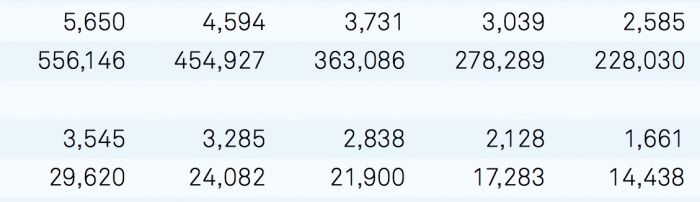
Welche Kombinationsschrift zur Input Sans (Font Bureau)
um nicht im eigenen Saft zu ertrinken, die Frage in die Runde: welche Schrift könntet ihr Euch für den Fließtext in Kombination zur Input Sans (Headline-Einsatz) vorstellen?
Um den Schwierigkeitsgrad noch etwas zu erhöhen – es sollte vorzugsweise auch ein serifenloser und wenn möglich nicht all zu teurer Font (max. 40,– € pro Schnitt) sein.
(Thema: Umwelttechnik, Ingenieurwesen)
Nachtrag: Meine Gedanken schwirren momentan in Richtung Univers (wirkt irgendwie abgestanden), Facit, FF DIN … hmmm.
Außerdem wird es eine zweite Variante in der FF Unit ohne Schriftmischung geben.
So – hat sich erledigt. Bin sowohl von der Input als auch von der Schriftmischung für dieses Projekt weg. Das wird zu kompliziert und die Input scheint mir ein eher schwer zähmbares Exemplar zu sein.
Könntet Ihr mit ruhigem Gewissen die Akkurat als Unternehmensschrift (auch Tabellen und Fließtext-Passagen, Druck und Web)  empfehlen, oder erlebt man da irgendwann das böse Erwachen? Ich finde formal ist sie eine echte Hausnummer, nur der Ausbau (z.B. fehlende Ziffernvarianten) bereitet mir ein wenig sorgen.
Also der Font (akkurat) scheint tatsächlich nicht viele Ziffernvarianten mitzubringen, wobei jetzt auch nicht so schnell rauszubekommen ist, ob die Basisversion proportionale oder Tabellenziffern mitbringt; wenn Dir die Schrift formal gefällt, ließe sich durch die Ergänzung mit der Mono-Version dieses Manko vielleicht beheben, weil da die Ziffern wohl auf jeden Fall tabellentauglich wären, würde sich wahrscheinlich auch stilistisch nicht schlecht machen (worum ging es: Ingenieure – die müssten ja darauf stehen). Prinzipiell würde ich Schriften von Grafikern ja erst mal misstrauen (ist die FF Unit denn noch im Spiel eigentlich).
Gut ausgebaute Alternativen müsste es eigentlich eine ganze Reihe geben, die so auf die älteren Grotesk-Modelle zurückgreifen (FF Bau zum Beispiel, vielleicht die Atlas Grotesk bei commercial type)
Von der Schriftmischung scheinst du abgekommen zu sein; vielleicht wär es ja auch einen Versuch wert, für Headlines etwas dezidiert ingenieurhaftes wie OCR-A oder -B für Überschriften oder Initialen mit einer Antiqua als Textschrift zu mischen (und auch da nichts humanistisches, sondern eher Modell Bodoni).
, für Headlines etwas dezidiert ingenieurhaftes wie OCR-A oder -B für Überschriften oder Initialen mit einer Antiqua als Textschrift zu mischen
oder die isonorm?
Ja, genau, so die Richtung für Schaugrössen, und eine richtige Schrift für Texte, wie ganz oben schon angedacht war.
Gerade drüber gestolpert, weil der Herr Übele gerade einen Newsletter verschickt hatte: Die Helsinki, sozusagen die finnische bzw. Übelesche DIN, das ginge dann wirklich mehr in Richtung Unternehmensschrift. http://www.ludwigtype.de/fonts/helsinki/overview … (gut ausgebaut und jede Menge features, & was ich ganz bemerkenswert finde, daß er ausserdem „Demofonts“ anbietet, also Schriftschnitte nicht nur im Fensterchen online zum Ausprobieren, sondern auch für Layoutzwecke versendet).
Könntet Ihr mit ruhigem Gewissen die Akkurat als Unternehmensschrift (auch Tabellen und Fließtext-Passagen, Druck und Web)
mittlerweile gibt es doch echt viele alternativen zur akkurat, du hast doch die ganzen listen angelegt :huhu:
die nitti grotesk z. b.
Also der Font (akkurat) scheint tatsächlich nicht viele Ziffernvarianten mitzubringen, wobei jetzt auch nicht so schnell rauszubekommen ist, ob die Basisversion proportionale oder Tabellenziffern mitbringt; wenn Dir die Schrift formal gefällt, ließe sich durch die Ergänzung mit der Mono-Version dieses Manko vielleicht beheben, weil da die Ziffern wohl auf jeden Fall tabellentauglich wären, würde sich wahrscheinlich auch stilistisch nicht schlecht machen (worum ging es: Ingenieure – die müssten ja darauf stehen). Prinzipiell würde ich Schriften von Grafikern ja erst mal misstrauen (ist die FF Unit denn noch im Spiel eigentlich).
Gut ausgebaute Alternativen müsste es eigentlich eine ganze Reihe geben, die so auf die älteren Grotesk-Modelle zurückgreifen (FF Bau zum Beispiel, vielleicht die Atlas Grotesk bei commercial type)
Vielleicht haben wir ja Glück und die Tabellenziffern finden sich auch in der Pro-Version. Ich hake noch mal bei der Foundry nach. Zusätzlich die Monoschnitte erwerben wäre zwar für das Erscheinungsbild ein passender Ansatz, das könnte aber dann doch das Budget sprengen.
Bzgl. FF Bau suche ich weniger nach Helvetica-Alternativen, sondern vielmehr eine Schrift mit Betonung der Senkrechten (habe hier mal eine Liste angelegt: Statische Alternativen zur DIN – Serifenlose mit senkrecht-gerader Linienführung). Dazu hatte ich mir neben der Input, DIN auch die Klavika, Cuitadella, Geogrotesque, Simplon, T-Star, FS Truman, … angesehen – aber da scheitert es meistens schon am klapprigen Mengensatz, wirkt zu unruhig oder dem Auftraggeber zu modisch.
Der Unterschied zwischen der Standard und Pro Version ist die erweiterte Sprachunterstützung in der Pro Version. Im Anhang finden Sie eine Übersicht.
Ein Specimen der LL Akkurat haben wir zurzeit nicht.
Gibt es eine Möglichkeit in einer PDF zu erkennen, ob der Text metrisch oder optisch ausgeglichen gesetzt wurde? Im Geschäftsbericht der Triodos Bank, welche auch die Akkurat als Hausschrift verwendet, sehen die Ziffern so gar nicht nach »tabellarisch« aus: